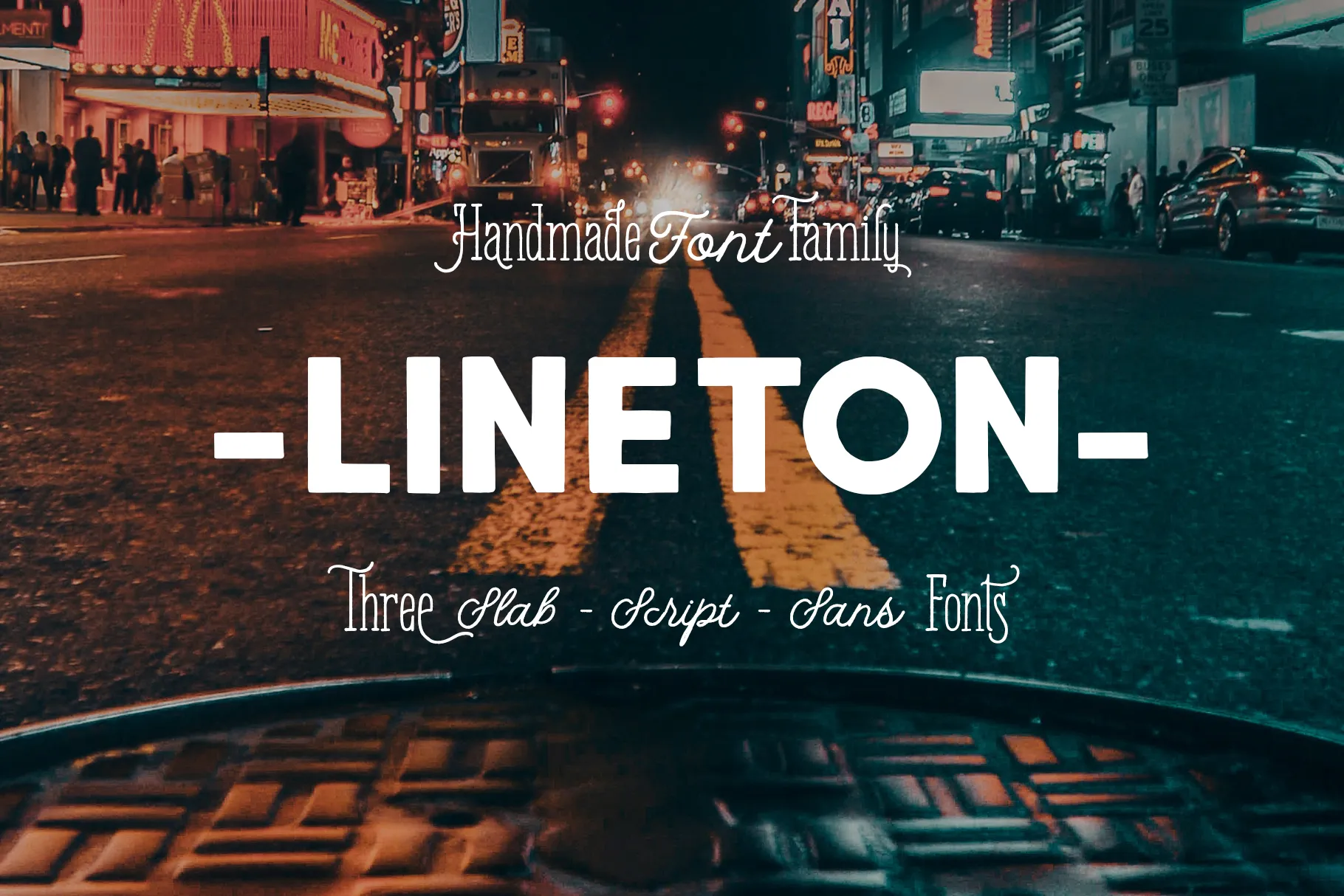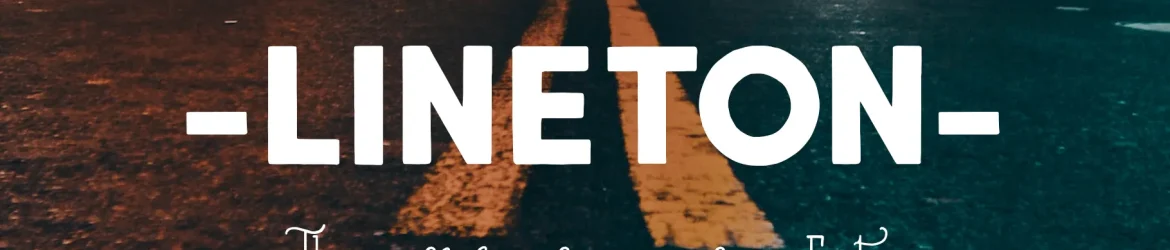
A Lineton é uma nova família de fontes sans-serif que apresenta elementos de tipo script e slab para oferecer uma variedade única. Ela traz uma vasta coleção de ilustrações aquarelas no formato vectorial, que você pode juntar perfeitamente com o design da fonte. A Lineton lhe dá algo inovador. O detalhe fornecido dará um aspecto cuidadosamente criado, e o combinação entre as fontes lhe dará a aparência de letra proferida por uma mão artística profissional. Esta font é perfeitamente adequada para uso em design de camisetas, logomarcas / marca, assinaturas, headlines, citações de letras e muito mais. Ela também vem em maiúsculas, minúsculas, sinais de pontuação, símbolos e numerais, conjunto alternativo estilizado, ligações e suporta multilinguagem.